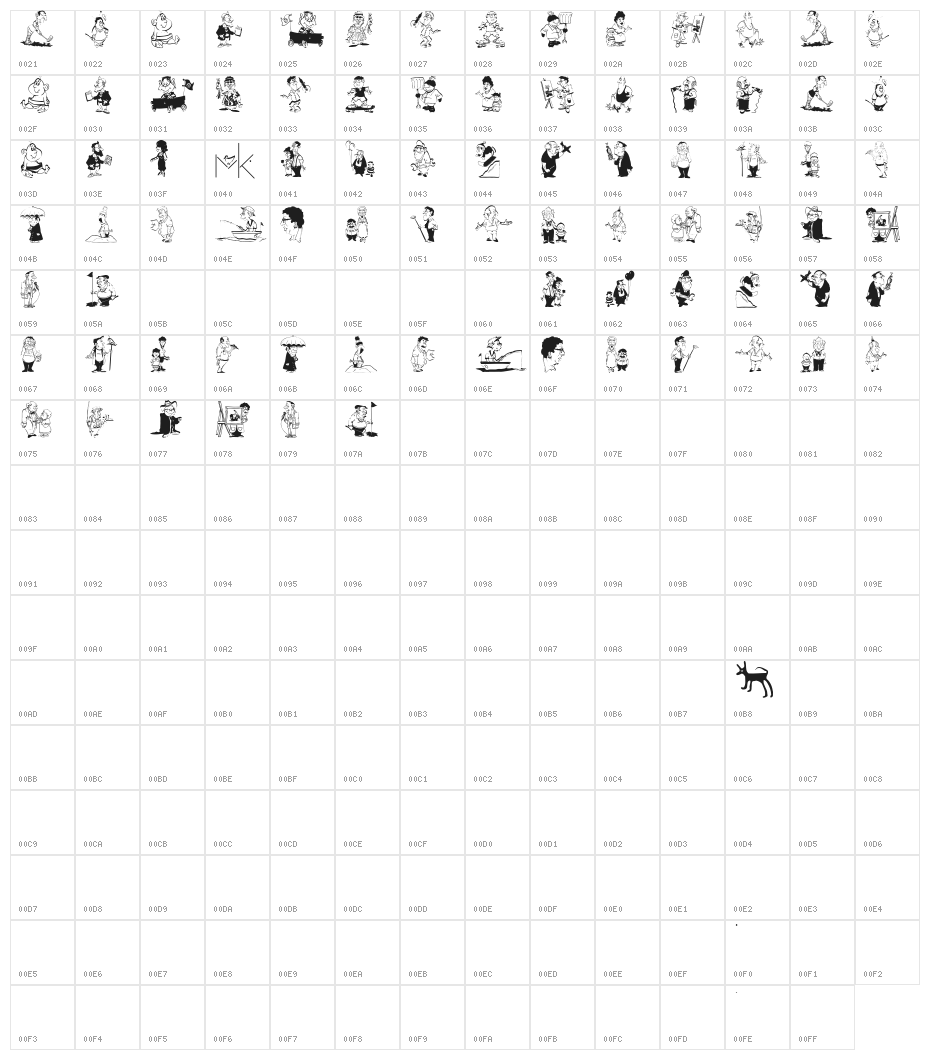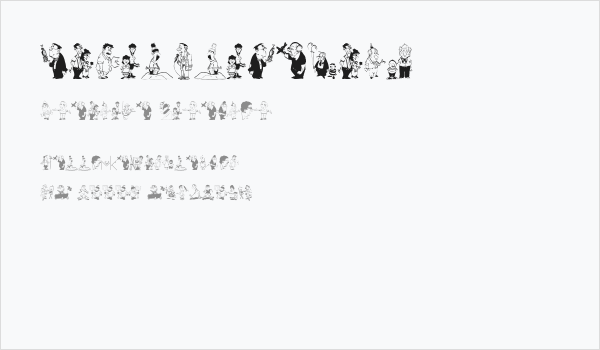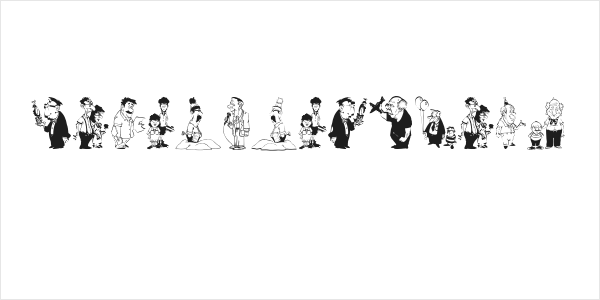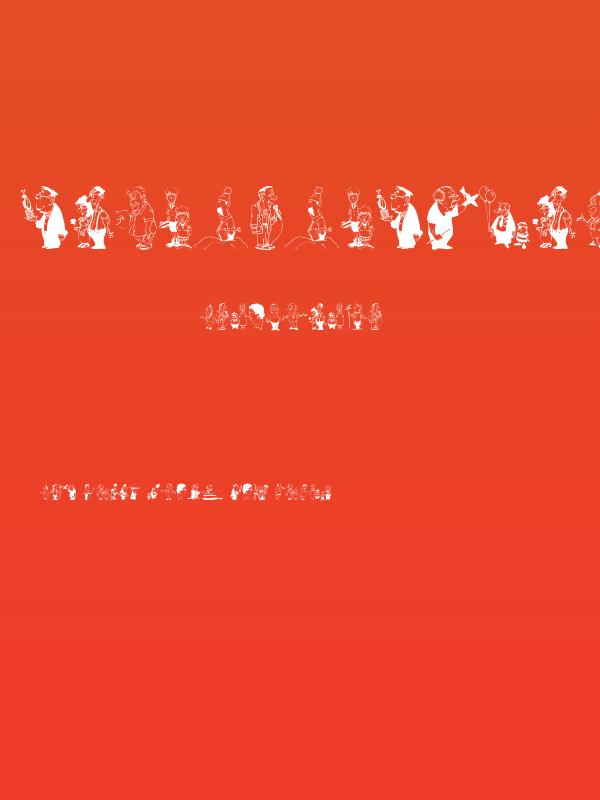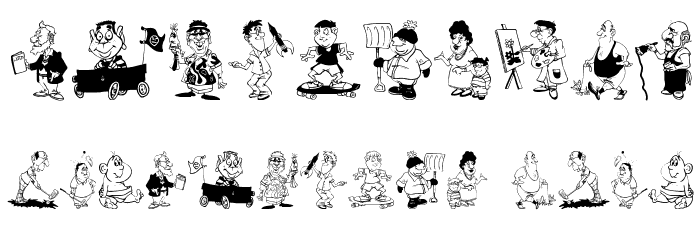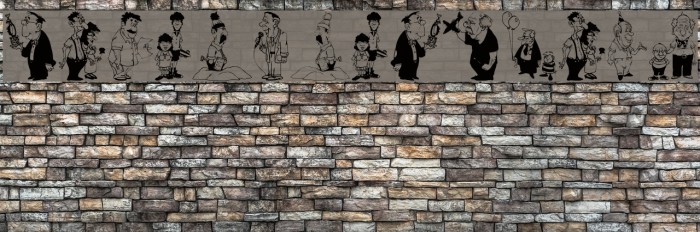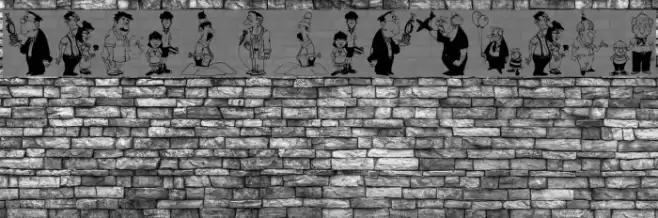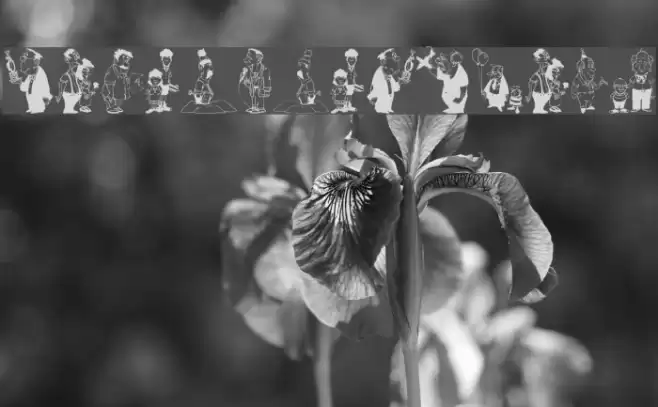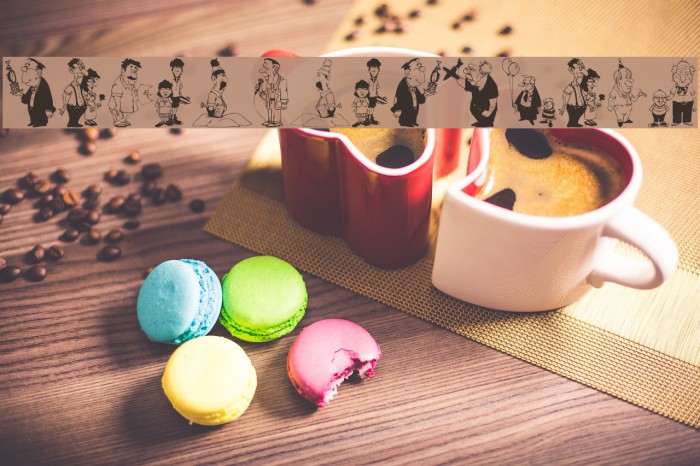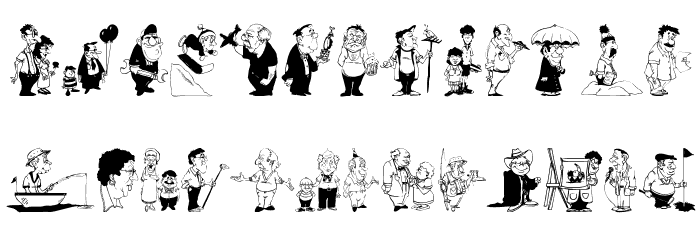
FamilyLifeBats Font
| Общий стиль | Playful and Humorous |
| Область применения | Illustrations, Comics, Educational Materials |
| Рекомендуемые проекты | Ideal for children's books, comic strips, educational materials, and playful greeting cards. |